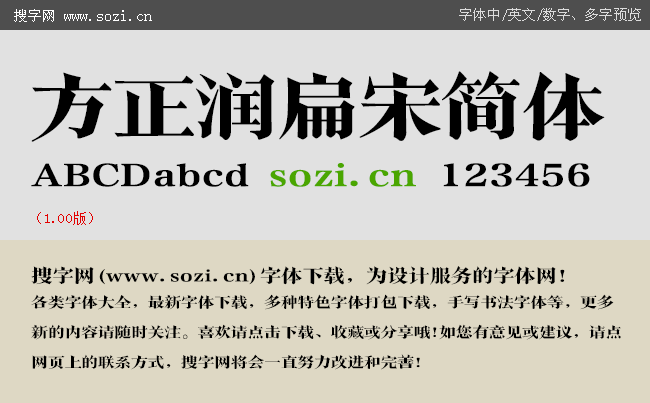
方正潤扁宋簡體
搜字網(wǎng)提供一款方正潤扁宋簡體字體下載,潤扁宋為扁方形宋體字,筆畫風(fēng)格借鑒了清代初期活字刻本,橫平豎垂,筆畫樸實敦厚結(jié)實硬朗,突出撇筆的銳意鋒利,折筆處理簡練果斷呈現(xiàn)濃厚的刀刻字味道,粗細對比強烈彰顯出字的特征,給人以很強的視覺沖擊力。整款字在傳遞安逸靜雅的書卷氣同時,也流露出樸素自然之感。適用于大標(biāo)題、小標(biāo)題、古文、牌匾以及廣告招貼等。